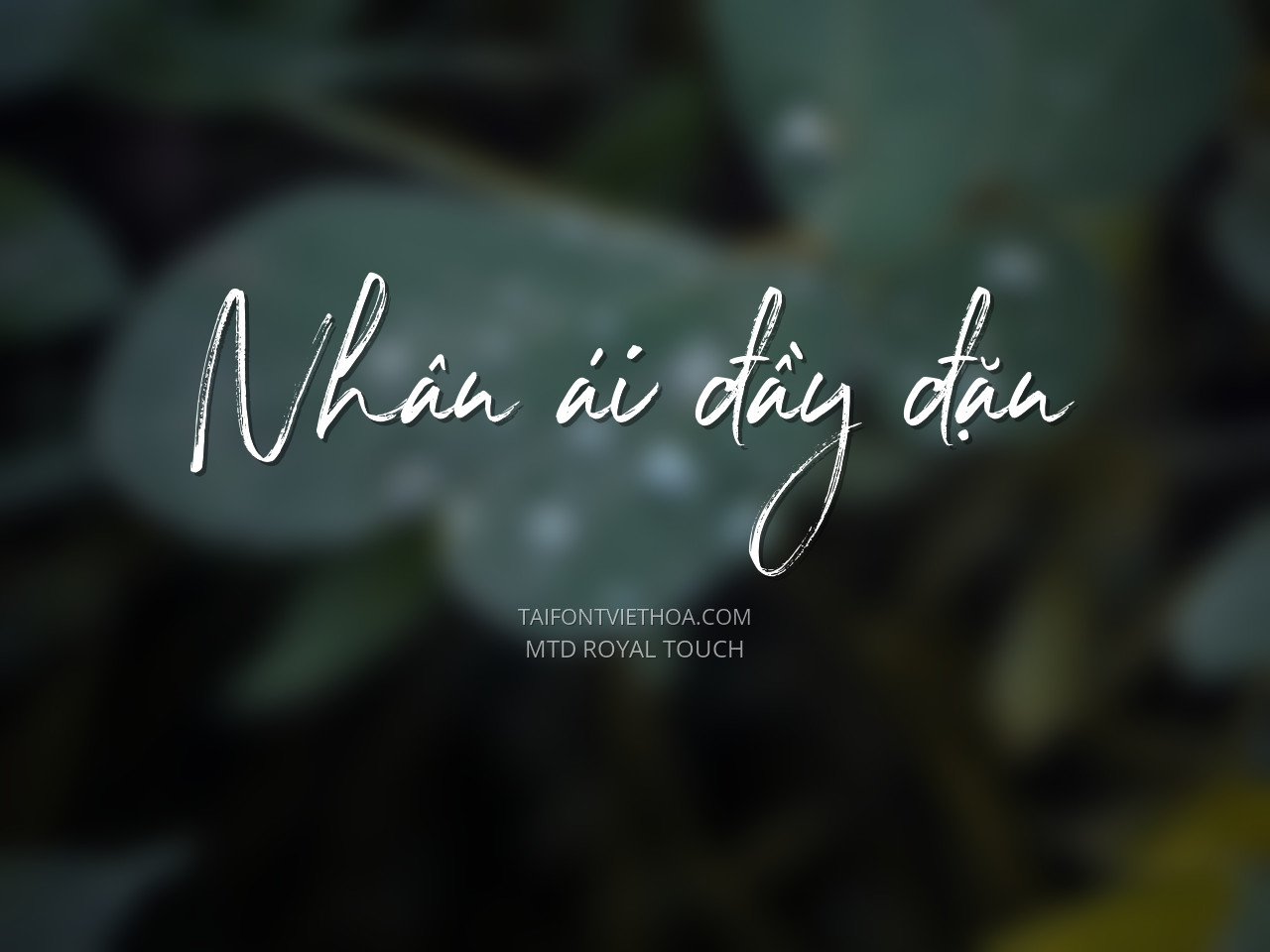
Font việt hóa MTD Royal Touch
Tác giả Font: Ivan Rosenberg
Giới thiệu về font Royal Touch
Royal Touch là một font script cao cấp mang phong cách hoàng gia, thanh lịch và đầy khí chất sang trọng. Được thiết kế bởi Motokiwo Type (MTD), font mô phỏng nét viết tay mềm mại nhưng có độ dày và độ nhấn mạnh rõ ràng, giúp thể hiện sự quyền quý, tinh tế và chuẩn mực trong từng dòng chữ. Các chi tiết được thiết kế tỉ mỉ, đường cong uốn lượn đầy nghệ thuật, rất lý tưởng cho các dự án cần tạo ấn tượng mạnh về sự đẳng cấp. Phiên bản Việt hóa do chính MTD thực hiện, hỗ trợ đầy đủ ký tự tiếng Việt cùng hơn 70 ngôn ngữ quốc tế, đảm bảo tính ứng dụng rộng rãi trong nhiều bối cảnh sử dụng.
Đặc điểm thiết kế và ứng dụng của font Royal Touch
Royal Touch sở hữu đường nét bay bổng, thanh mảnh kết hợp với các ligatures mượt mà và swashes uốn lượn tự nhiên. Font có tỷ lệ chữ hài hòa, độ tương phản giữa các nét vừa đủ để tạo sự nổi bật mà vẫn giữ được sự trang nhã. Nhờ đặc điểm này, Royal Touch đặc biệt phù hợp cho các thiết kế như: thiệp cưới sang trọng, logo thương hiệu thời trang, bộ nhận diện mỹ phẩm cao cấp, hoặc typography nghệ thuật.